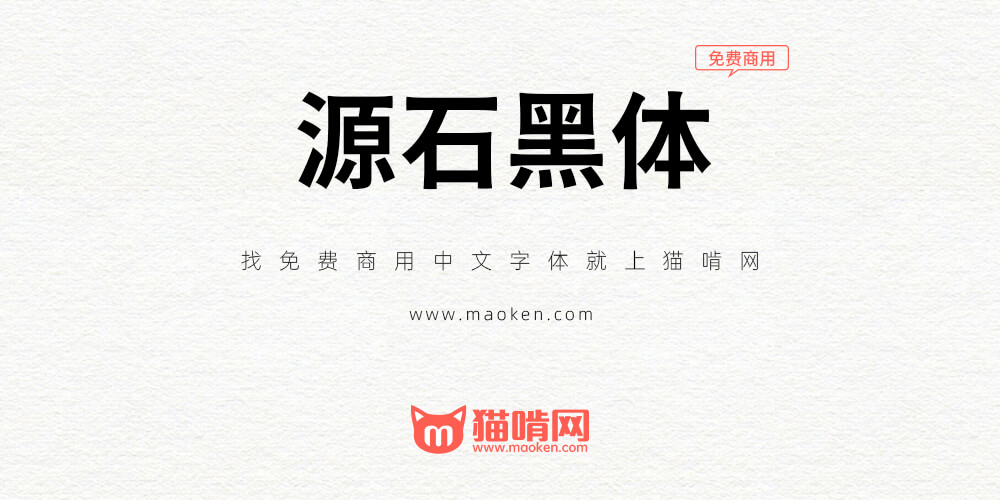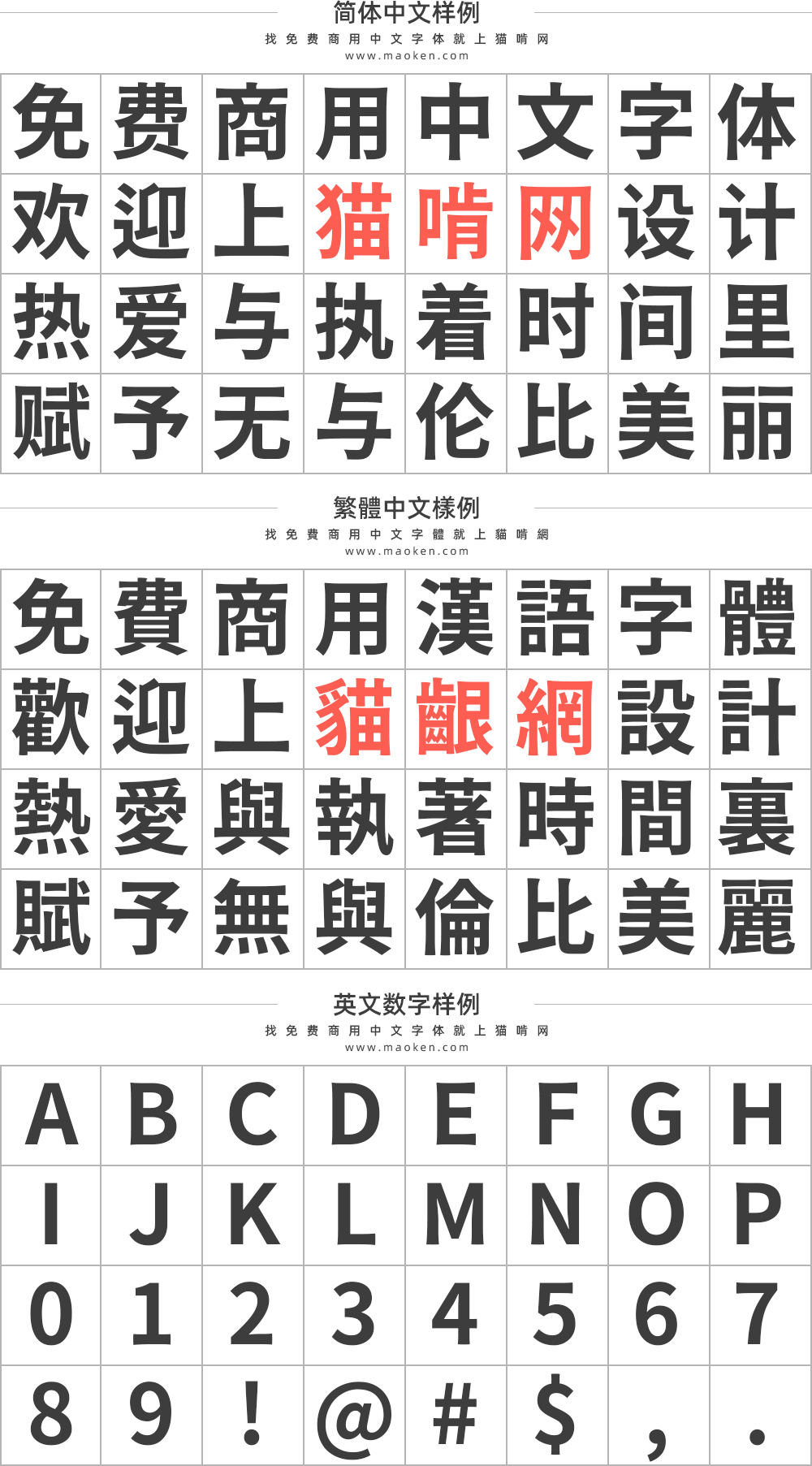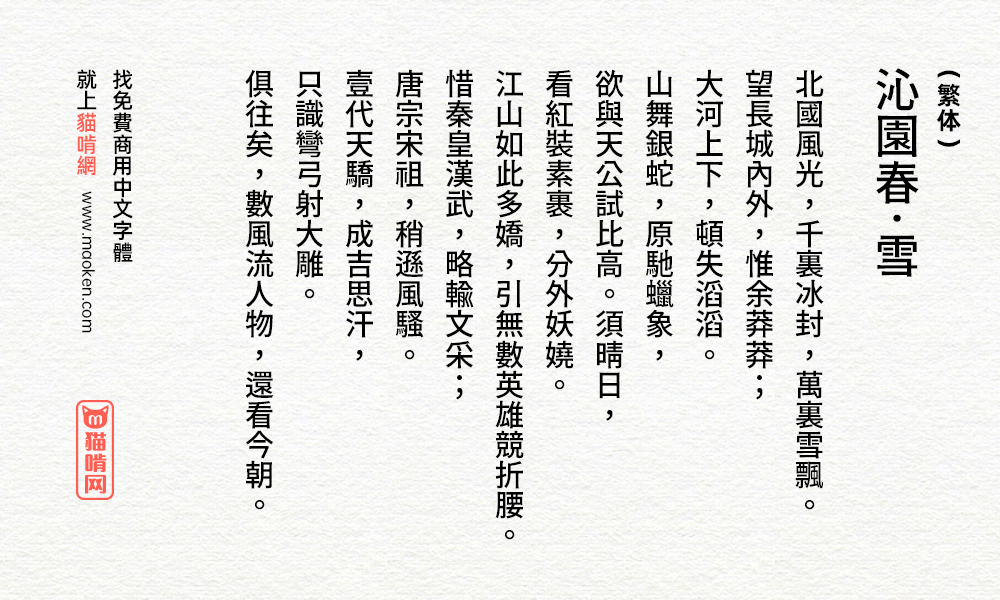
源石黑体:基于思源黑体改造的复古风格黑体字型 免费商用
字体作者:But Ko (中国台湾) 字体字重:5个
话说这几年有好多的黑体陆续面世,但是现在的黑体设计一个比一个干净,一个比一个锐利。实在令人怀念起那传统而带有温度的黑体。有喇叭口,还有那若隐若现的衬线……而现在这款源石黑体则尝试重现较早年代的比较复古的黑体风格,较有温暖的气息。
源石黑体是台湾设计师But Ko基于思源黑体改造的一款字型。它保留思源黑体所支持的所有汉字(包或日、韩文汉字与简体字),一般会用到的汉字几乎不会有缺字问题。 但是由于是程序自动生成的字体,所以有些字可能会存在某些笔划的错误,请大家在正式使用时检查清楚。
好像和思源黑体区别不大
好像和思源黑体没多大区别
在手机上替换了这款字体,没想到意外的好看。